Шрифты “от руки”: учимся рисовать
В эпоху социальных сетей и смартфонов в скором времени в обществе станут появляться люди, которые лишь понаслышке будут знать, что такое письма от руки. Меньше всего в современном мире человек при желании общаться с родными и близкими заботится теперь о написании бумажных писем.
Проще и быстрее отправить короткое текстовое или звуковое сообщение, но что если вам захочется выразить свои чувства при помощи писем от руки?
Как воспользоваться рукописным текстом, какие рукописные шрифты бывают и где их найти, об этом поговорим в сегодняшнем посте. Единственное, что мы можем сказать с полной уверенностью, даже непрофессионал и человек далекий от понимания каллиграфии сможет воспользоваться приведенными ниже примерами, чтобы создать красивое, яркое и незабываемое письмо. Методы отлично подойдут и тем, у кого от природы ужасный почерк. 😉
Начнем с пошагового плана. И для начала выберем
Всему нужна основа
Прежде всего вам необходимо набросать структуру своих будущих писем. Одна из самых распространенных ошибок – игнорирование начальных шагов, спешка и жгучее желание добиться результата как можно быстрее. Ваше письмо и в целом стиль рукописного ввода будут выглядеть привлекательнее, если сначала создать скелет.
После подготовки основы для будущего рукописного сообщения можно переходить к буквам. Здесь также не стоит торопиться, тщательно прорисованный элемент требует усердия и времени.
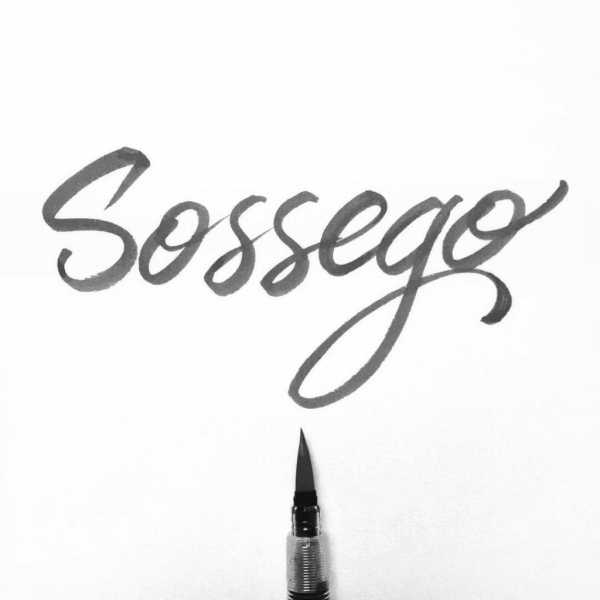
Дальше можно оживить буквы и слова элементами выбранного шрифта. Не бойтесь экспериментировать с кривыми и плавными линиями и т.д.
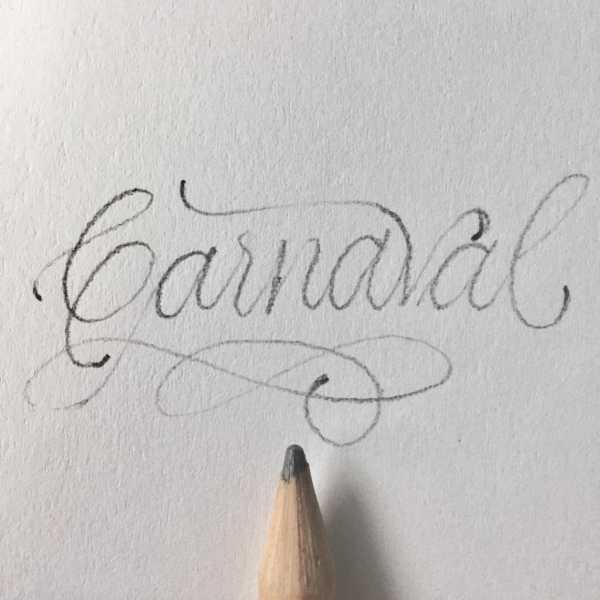
ТОП-15 рукописных шрифтов
Если вы не хотите изучать каллиграфию самостоятельно, но хотите использовать красивые рукописные шрифты на своем сайте, воспользуйтесь уже готовыми наборами шрифтов. Мы подготовили подборку из 15 лучших рукописных шрифтов от TemplateMonster.
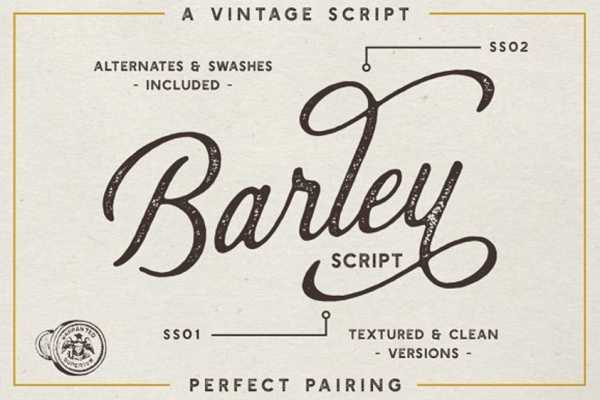
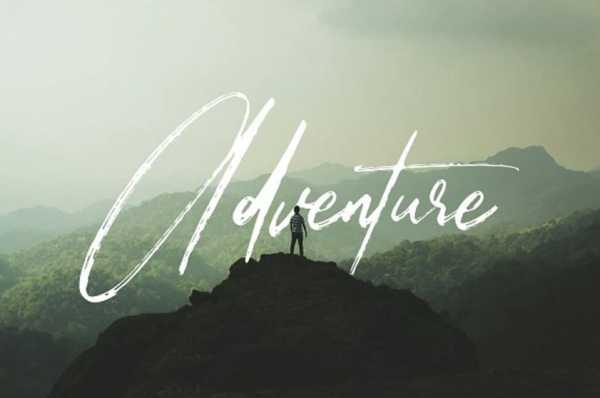
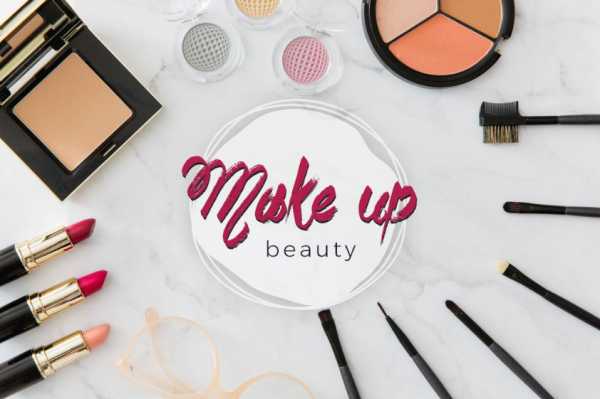
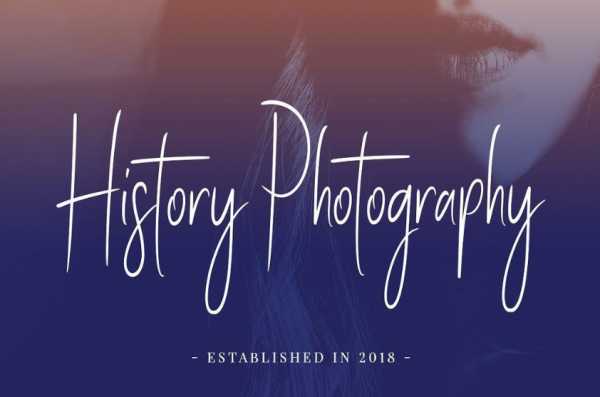
ТОП-15 рукописных шрифтов 2019
Я настоящий фанат типографики, и трачу много времени на поиск и экспериментирование со всеми видами различных типов шрифтов и стилей.В этом смысле, я также пытался создать собственные шрифты, и должен сказать, что любой человек, обладая небольшим опытом, может это сделать.
Fontstruct
Fontstruct это веб-приложение, являющееся замечательным средством для создания шрифтов, особенно если вы новичок в этом деле. Для создания шрифтов, пользователям нужно зарегистрироваться, но графический интерфейс настолько просто и удобен в использовании, что вы начнете пользоваться им моментально.
Fontstruct встречает пользователей MS Paint-подобным окружением, где они могу использовать «кирпичики», которые по существу являются шаблонами, помогающими создать избранный вами дизайн. Есть десятки кирпичиков, на выбор, каждый из которых может предоставить создателям свою уникальную особенность, для добавления к шрифту.
Несколько дополнительных базовых инструментов включают в себя: ластик, инструмент создания линии/прямоугольника и инструмент «рука», позволят создавать шрифты точно и профессионально.
Fontsrtuct содержит символьные модели более чем 20 различных языков.
Во время создания своего шедевра, Fontsrtuct предоставляет возможность напечатать и протестировать результат, в условиях реального времени, что, несомненно, удобная функция как для новичков дизайнеров, так и для профессионалов.
После того как ваш шрифт будет готов, вы можете скачать его (в формате TrueType) и/или выложить в общий доступ, через галерею. Здесь пользователи могут публиковать, голосовать и скачивать шрифты, повсюду создавая сообщества любителей типографики.
FontForge
Если же для создания шрифтов, вы предпочитаете десктопные приложения, давайте рассмотрим FontForge: замечательную бесплатную программу, позволяющую создавать собственные шрифты. Она более замысловата в сравнении с Fontstruct, и содержит большое количество настроек и инструментов.
Пользователей встречает растровое изображение знаков и символов, которые можно формовать и переделывать, в соответствии с желаемым дизайном. FontForge совместим с множеством различных форматов шрифтов, включающих в себя TrueType и Opentype.
Я бы также рекомендовал к прочтению отличное руководство, от создателей FontForge, которое поможет вам при создании шрифтов. Есть версии программы для Windows, Mac, и Linux, однако пользователи Windows также должны установить Cygwin, являющееся бесплатным Linux окружением для Windows, необходимым для запуска FontForge.
Сила типографики. Потрясающие шрифтовые рисунки.
Шрифты — неотъемлемая часть дизайна. Их многообразие и неуемная фантазия авторов уже давно сделали шрифты чем-то большим, чем просто средство передачи текстовой информации. Шрифты стали и средством графической информации, уникальным способом влияющим на восприятие картины зрителем. Мы уже публиковали серии портретов, выполненные шрифтами. Представляем вашему вниманию очередную подборку типографических шедевров.